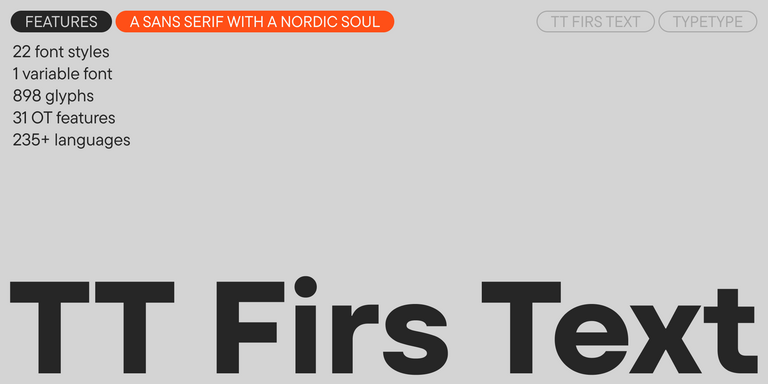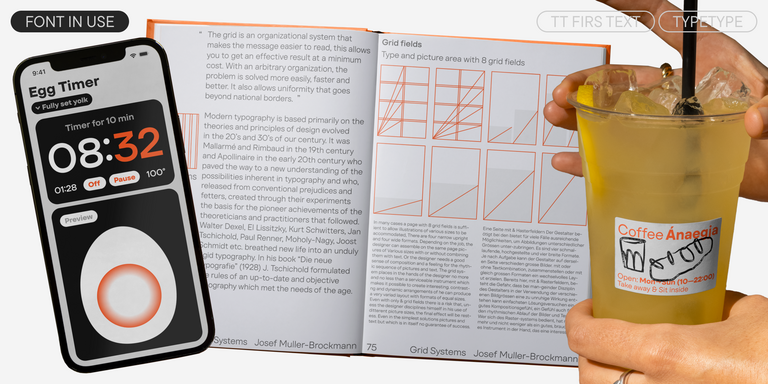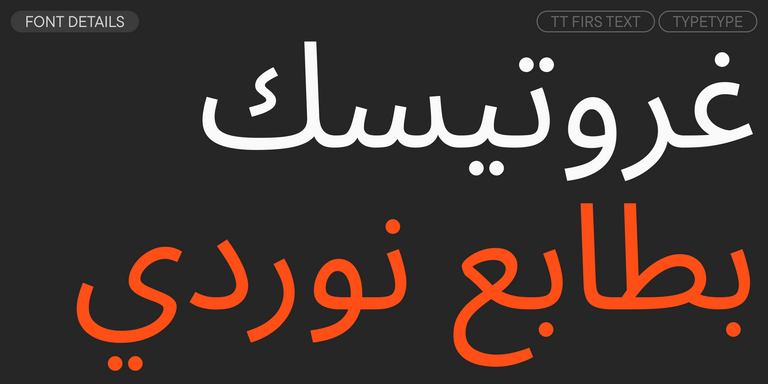
خطوط مشابهة لـ Paris Metro
إذا كنت قد سئمت من الخطوط الشائعة الاستخدام وتبحث عن خطوط مشابهة لـ Paris Metro، فاطلع على أفضل البدائل المجانية للتجربة التي تقدمها Paris Metro، والتي تتميز بخصائص مشابهة بالإضافة إلى تصميمات جديدة وفريدة من نوعها. تنتمي بعض هذه الخطوط إلى نفس الفئة، بينما يُمكن أن تكون الأخرى مناسبة لنفس المهام أو تحمل سمات مشابهة، ولكنها تتميز بتفاصيل أو نسب مميزة.
في TypeType، ستجد خطوطًا مبتكرة مثل Paris Metro بل وأفضل: إليك بعض البدائل الرائعة وغير الشائعة لخط Paris Metro. استخدم هذه القائمة لأعلى الخطوط جودة التي تشبه Paris Metro كما تريد. تقدم قائمتنا مجموعة واسعة من الخيارات لاختيار أفضل خط يناسب مشروعك ويضفي لمسة منعشة على تصميماتك. جميع الخطوط الموجودة في هذه المجموعة متوفرة بأشكال متعددة وبأسعار معقولة، لتتمكن من العثور على ما يناسب احتياجاتك بالكامل!
ابحث عن بديل رائع لخط Paris Metro وحاول إعادة خلق نفس الحالة المزاجية والتأثير الذي تسعى لتحقيقه باستخدامه في تصميماتك. كل خط معروض في هذه الصفحة هو بمثابة نسخة مشابهة لخط Paris Metro، يكاد يكون مطابقًا له.
TT Gertika is a geometric sans serif with a dynamic character and a dancing rhythm. This font’s idea originates from the lettering featured on an American poster from the late 1930s.
TT Carvist—peculiar, playful, and courageous—this font does an excellent job of grabbing attention!
We have released a brand-new font. Meet TT Firs Text—a geometric sans serif with a Nordic character!
TT Wellingtons is an attempt to combine the style of English humanist sans serifs of the early 20th century with the requirements for modern geometric grotesques.
When designing TT Mussels, we paid great attention to the possibility of imposing large arrays of text, and we can state that TT Mussels is a rare type of technological text fonts.
TT Bricks is the answer for lovers of Soviet culture. We’ve tried going back a hundred years and rethinking the constructivist era.